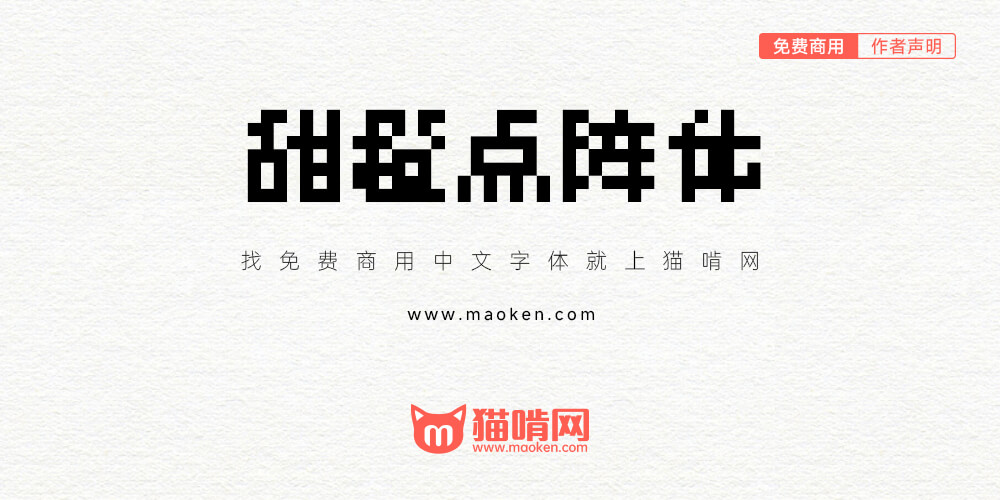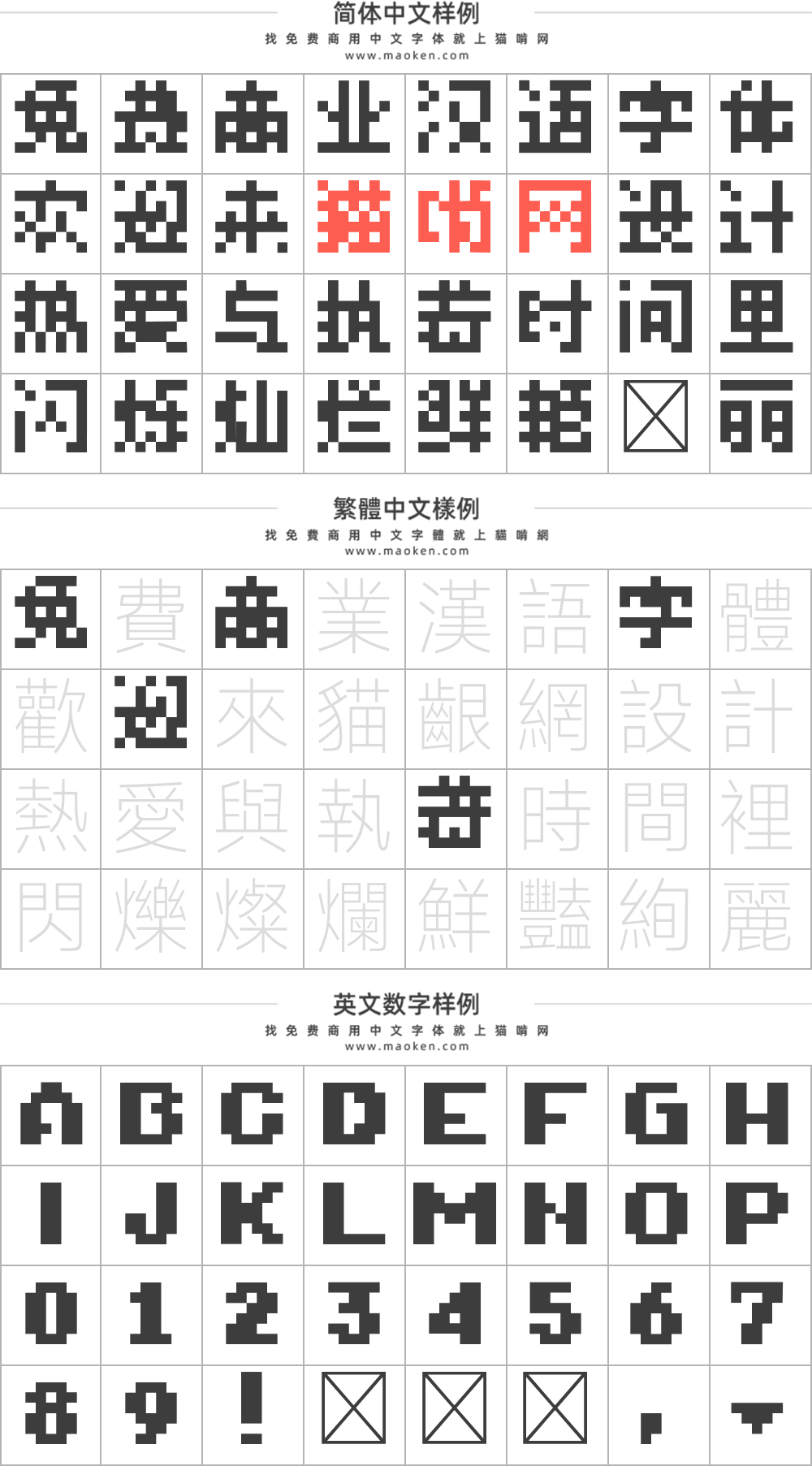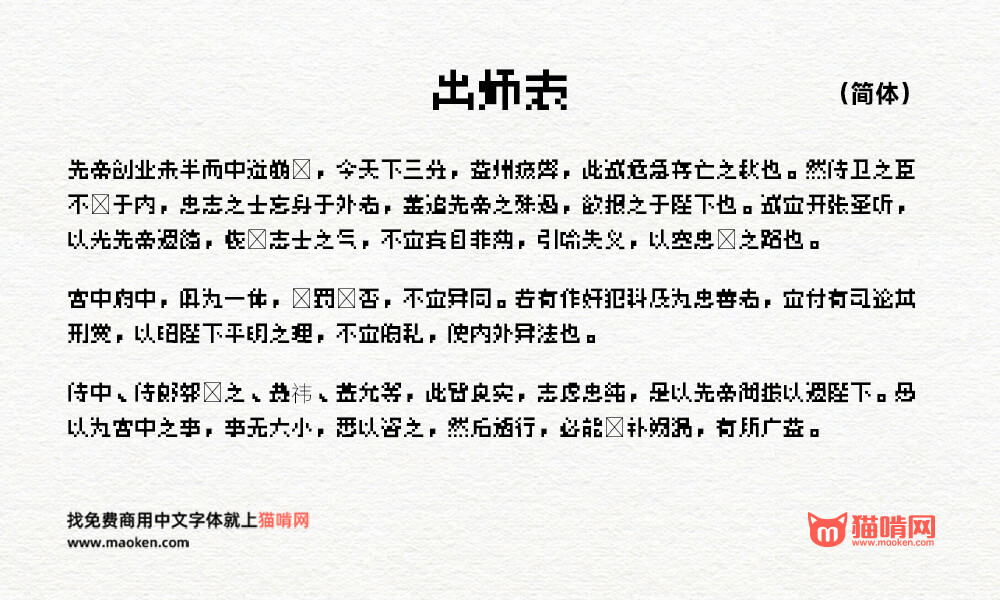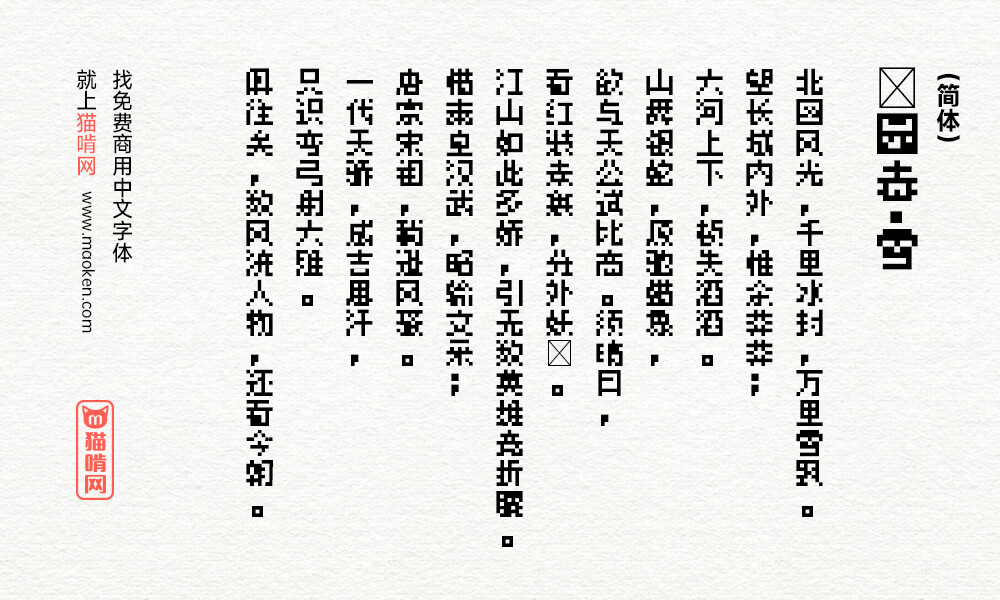
| 字体作者:DOUOA (中国大陆) | 字体字重:1个 |
作者介绍:DOUOA,来自哔哩哔哩,游戏制作爱好者
字体介绍:甜橙点阵体,7像素点阵字体,清晰度优于多数同类型字体,适用于游戏、软件界面等设计,支持简体中文,由ZFONT修正字体名称、字高和ROS信息
挺好一 7px 字体,真可谓是百花齐放、百家争鸣了
7px真的太极限了